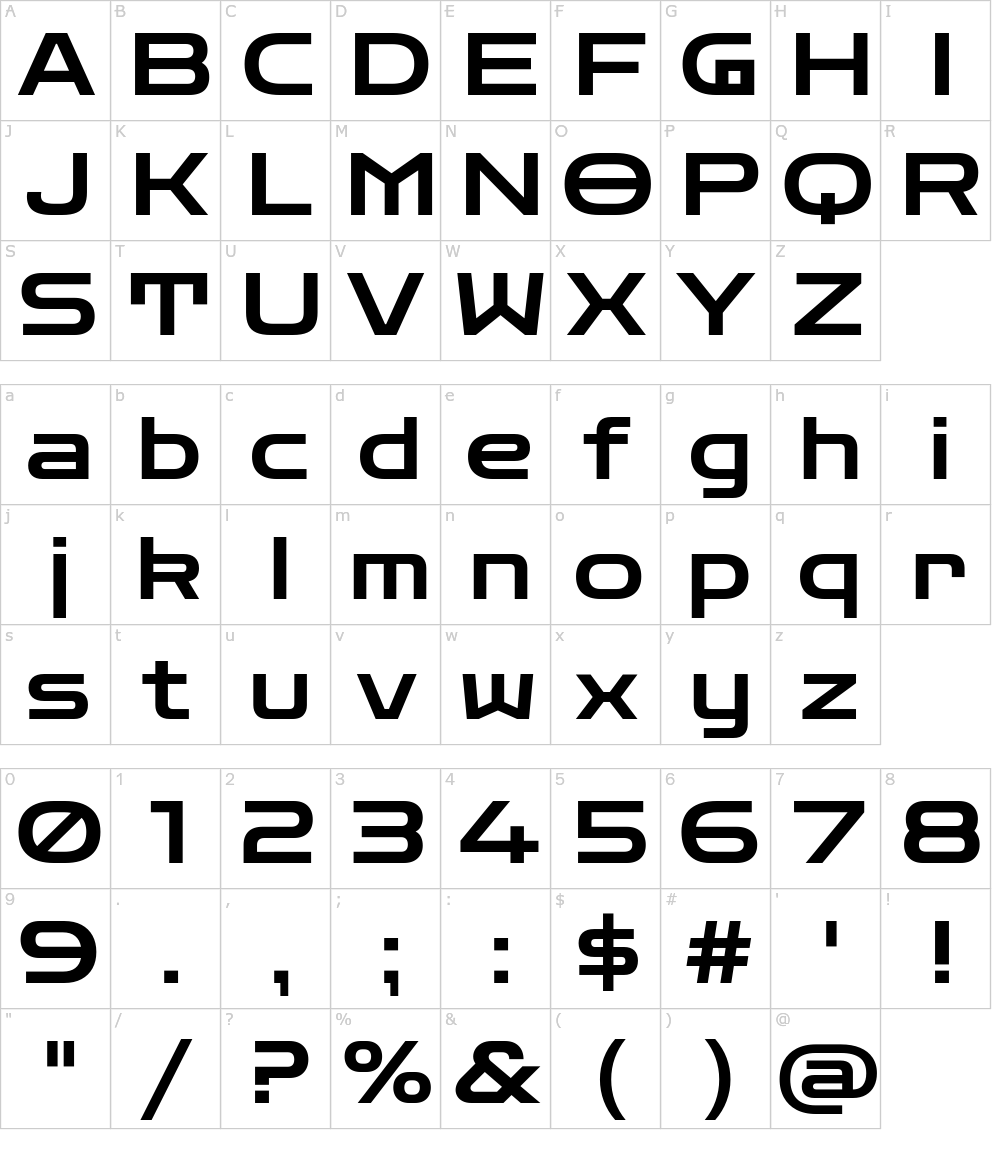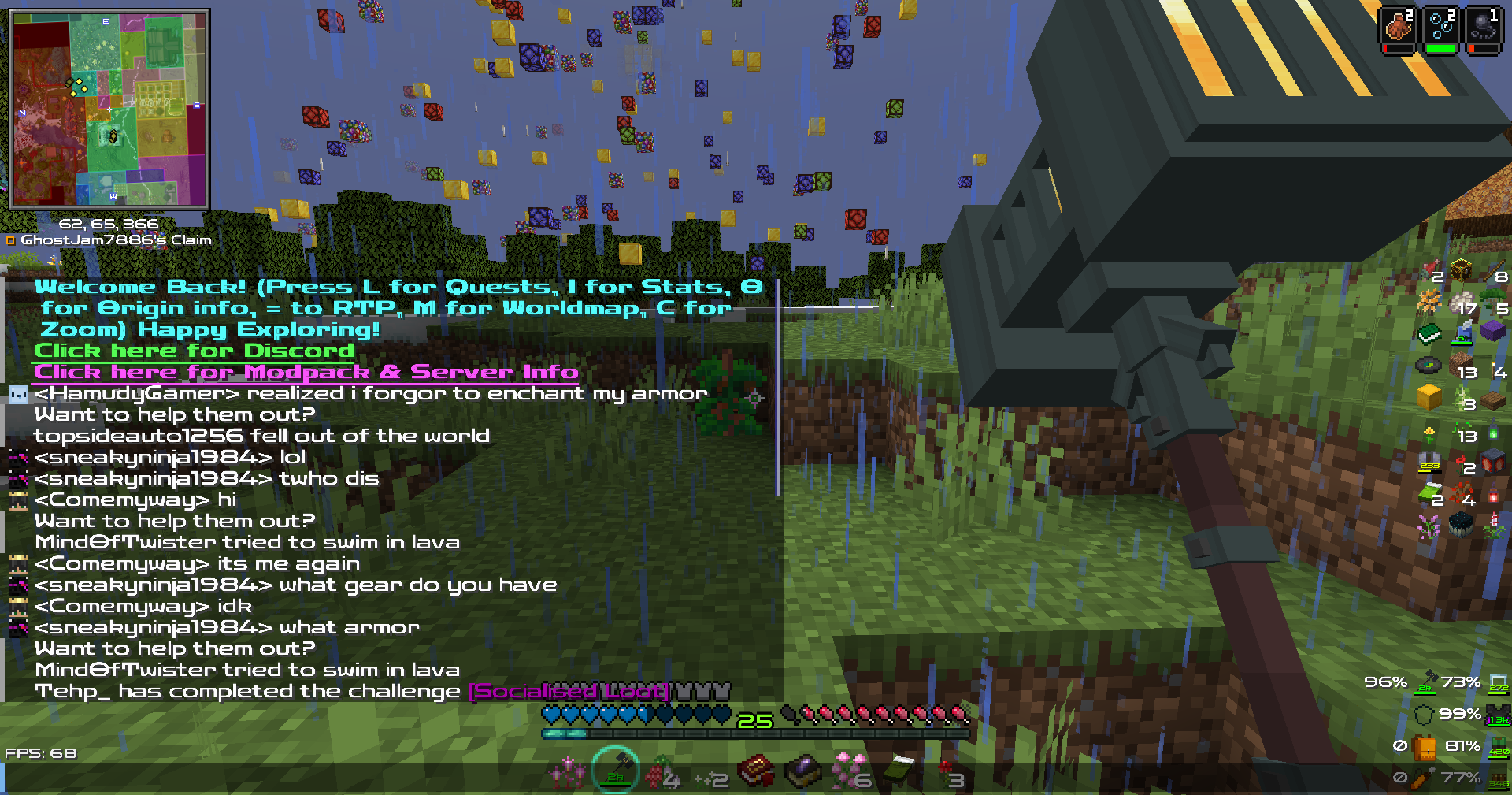
Zen Font для Minecraft: Чистый и Читаемый Шрифт
Если вы устали от стандартного шрифта Minecraft и хотите сделать текст в игре более четким и стильным, Zen Font — отличное решение. Этот шрифт создан для улучшения ванильного опыта, делая текст более читаемым и эстетичным.
🔍 Что такое Zen Font?
Zen Font — это кастомный шрифт для Minecraft, основанный на Zen Dots Google Font от Yoshimichi Ohira. Первоначально он был разработан для модпака DarkRPG, но теперь доступен для всех игроков.
📌 Основные особенности:
✔ Четкость и минимализм — шрифт легко читается даже в динамичных ситуациях.
✔ Стильный дизайн — идеально подходит как для ванильной игры, так и для модифицированных сборок.
✔ Разрешение 32x — улучшенная детализация без потери производительности.
🖼️ Как выглядит Zen Font в игре?
(alt: Скриншот Minecraft с Zen Font — чистый и современный текст в интерфейсе)
(alt: Сравнение стандартного шрифта и Zen Font в чате и инвентаре)
Шрифт отлично сочетается с любыми текстурами и модами, не перегружая интерфейс.
🎮 Где лучше всего использовать Zen Font?
Этот шрифт отлично подходит для:
- РПГ-модов (например, DarkRPG).
- Серверов с большим количеством текста (чат, квесты, интерфейсы).
- Игроков, ценящих минимализм без лишних деталей.
🏁 Заключение
Zen Font — отличный выбор для тех, кто хочет улучшить читаемость текста в Minecraft без лишних изменений геймплея. Простая установка, стильный дизайн и совместимость с большинством модов делают его одним из лучших вариантов для кастомизации интерфейса.